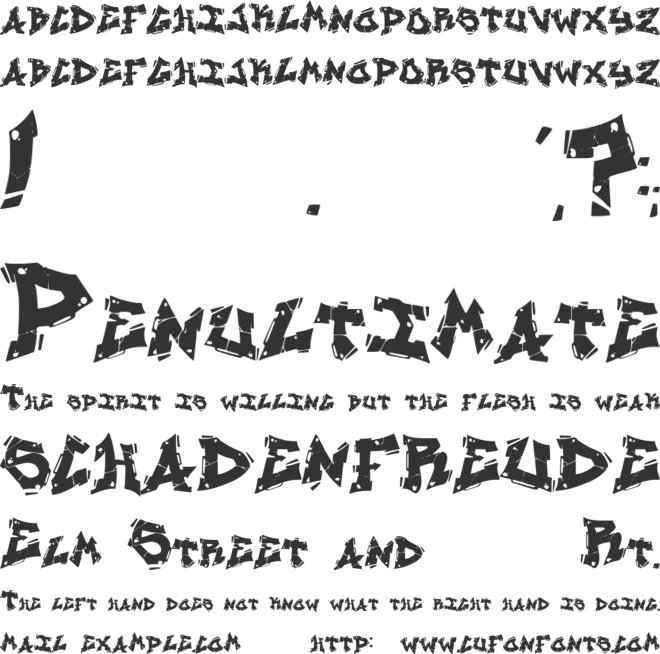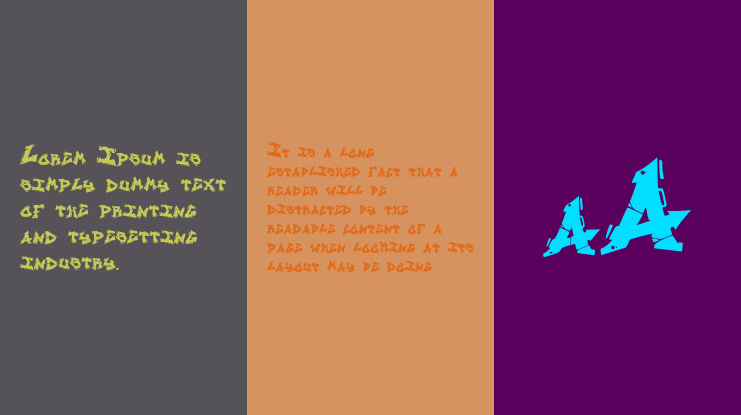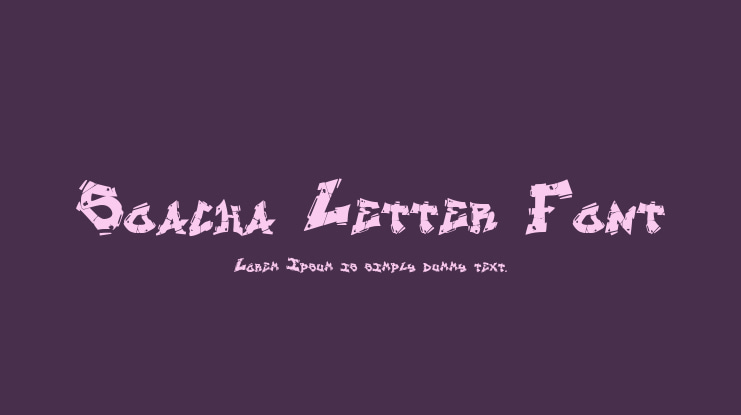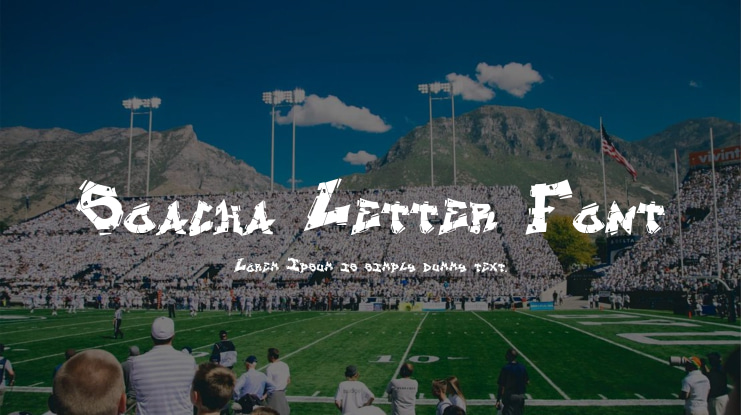
Soacha Letter Font
Esta fuente tipográfica fue elaborada a partir de el análisis de la mayoría de los grafitis que se encuentran en Soacha-Cundinamarca Colombia. Con el objetivo de generar apropiación por el grafiti Suachuno.